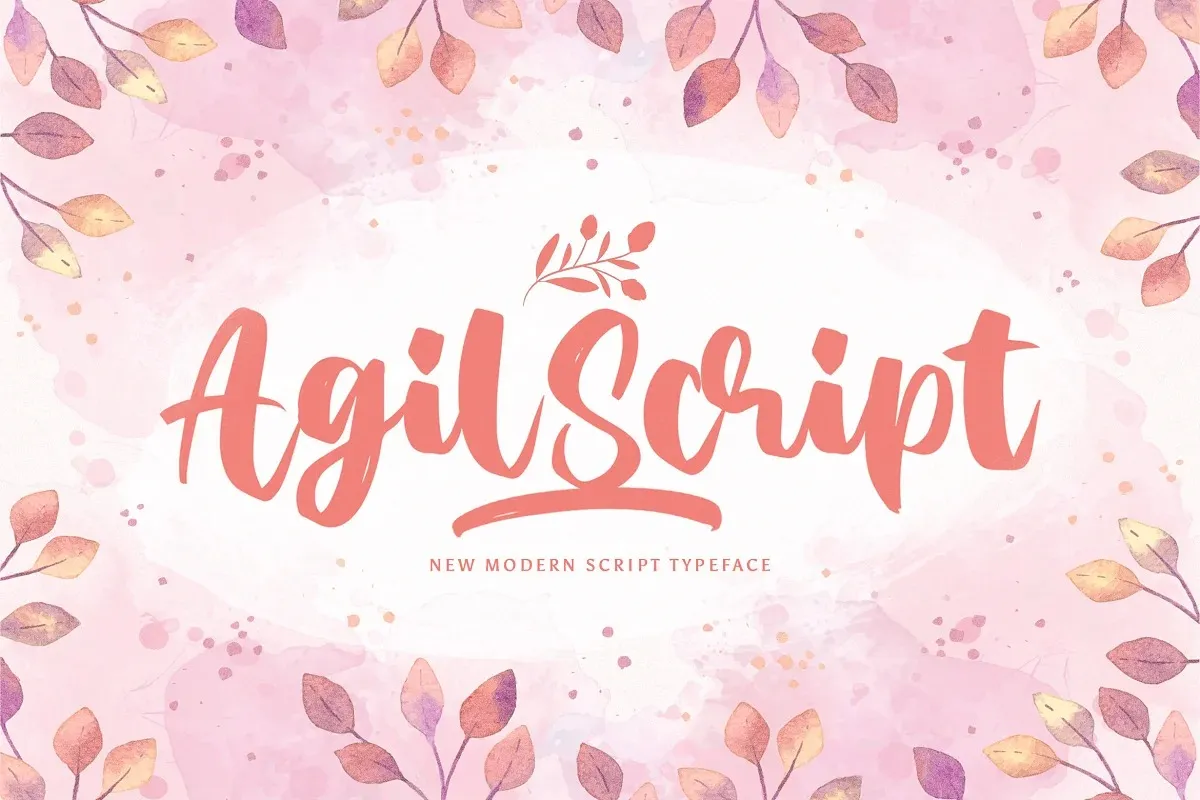
Agil Script Font
A Agil Script Font é uma fonte de script criada pela StringLabs em 2021. Ela é uma letra única e texturizada que se destaca pelo seu equilíbrio perfeito entre caracteres, tornando-a perfeita para um amplo range de projetos. Esta fonte possui uma beleza natural que complementa qualquer ideia criativa e a torna realista e viva em seus designs. Adicione Agil Script à sua galeria de ideias inovadoras e note como ela dá vida aos seus desenhos! Esta opção única pode se tornar o diferencial perfeito para seu próximo projeto visual.